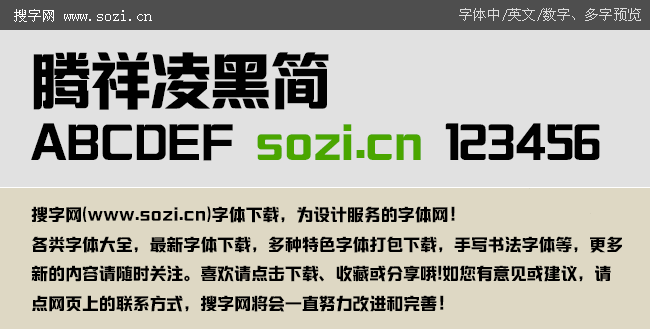
騰祥凌黑簡(jiǎn)
搜字網(wǎng)提供一款騰祥凌黑簡(jiǎn)中文藝術(shù)字體下載,騰祥凌黑整體字形筆畫均衡,風(fēng)格現(xiàn)代,風(fēng)格清晰端正,適合標(biāo)題用字,可用于印刷出版、包裝設(shè)計(jì)、廣告設(shè)計(jì)、網(wǎng)頁(yè)設(shè)計(jì)等。